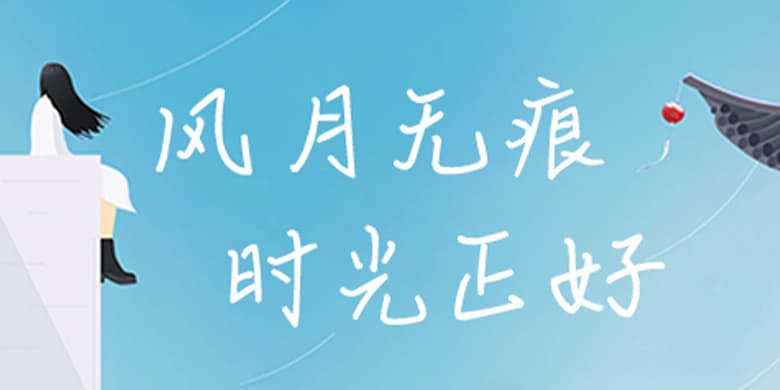
品牌:方正手迹设计师:刘晔发行时间:2020字库编码:大陆简体(GB2312-80)分类:常规书写·硬笔字体属性:精品字
风月无痕是一款小清新风格的手写体。该字体整体松紧适中,大小均匀。笔画纤细,充满着年轻,活力的气息。该字体适用于文艺类的书刊、品牌广告和产品包装设计,以及社交网络的个性化用字。
品牌:方正手迹设计师:刘晔发行时间:2020字库编码:大陆简体(GB2312-80)分类:常规书写·硬笔字体属性:精品字
风月无痕是一款小清新风格的手写体。该字体整体松紧适中,大小均匀。笔画纤细,充满着年轻,活力的气息。该字体适用于文艺类的书刊、品牌广告和产品包装设计,以及社交网络的个性化用字。